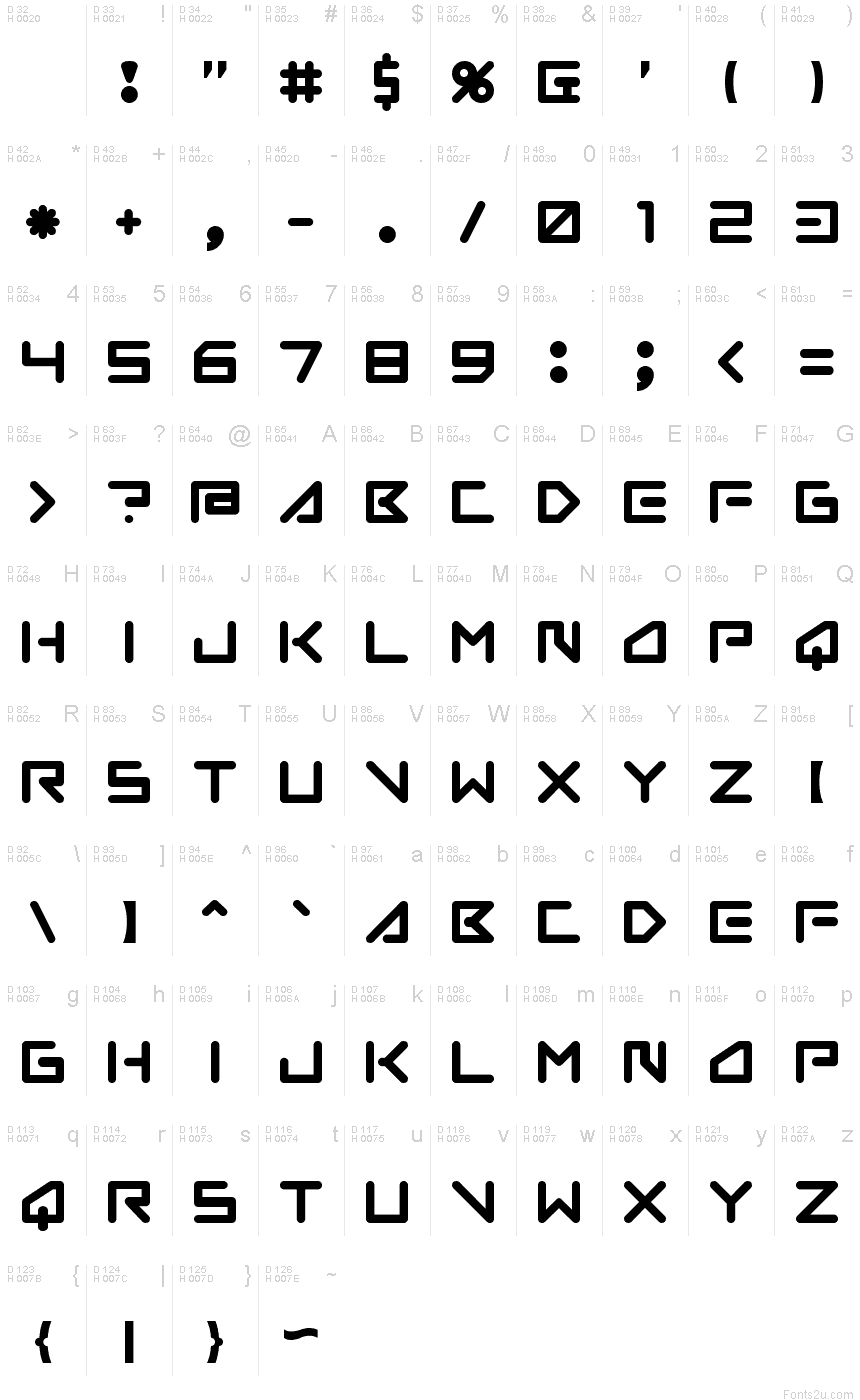
Náhled písma Insane hours 2
Insane hours 2 od Jakoba Fischera je bezplatné techno-futuristické písmo typu display. Jeho masivní, trubkovité tahy a ostře lomené spoje připomínají neonové trubice vytvarované do podoby písmen, což textu dodává mechanický a výrazný rytmus, který díky zaobleným koncům působí stále přátelsky. Díky těsnému a rovnoměrnému rozestupu tvoří slova pevné, futuristické bloky – skvělá volba, když potřebujete, aby vaše sdělení zapůsobilo na první pohled.
S fontem Insane hours 2 získají vaše titulky a loga okamžitě noční sci-fi atmosféru, která se skvěle hodí na obaly her, klubové či EDM letáky, plakáty na technologické akce, úvodní obrazovky aplikací nebo výrazné náhledy na YouTube. Toto bezplatné písmo nejvíce vynikne ve velké velikosti s dostatečným volným prostorem kolem; pro hlavní text jej zkombinujte s čistým geometrickým bezpatkovým písmem, aby layout zůstal ostrý a čitelný.